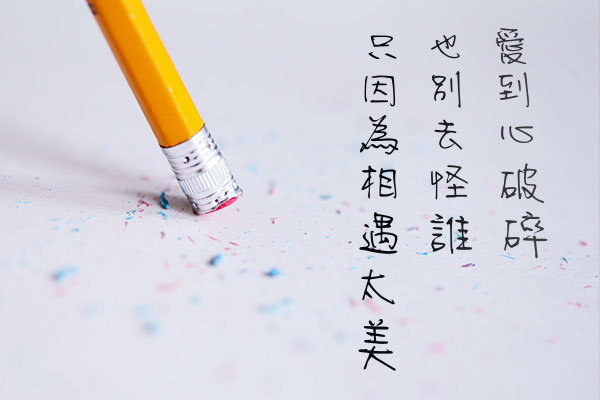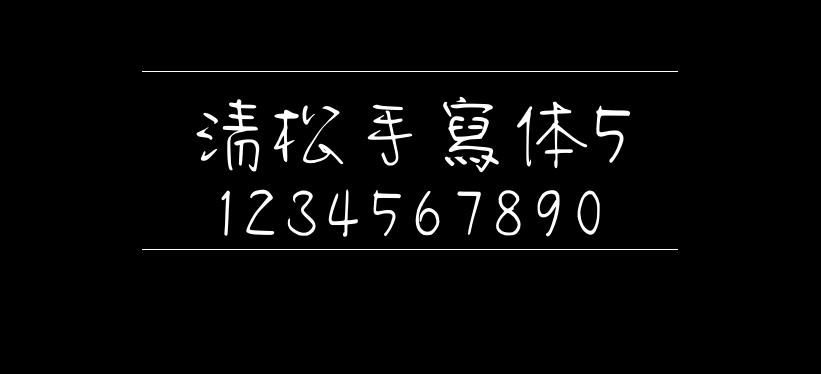
清松手写体5
清松手写体5(JasonHandwriting5、清松手寫體5)是游清松推出的第5套手写字型,作者在稿纸上用原子笔手写,透过“守写字”网站产生出初稿字型档,再字体软件制作加工而成的手写字型。
清松手写体5为手写字型,没有一般电脑字型的生硬感,多了几分手写般的自然感。不论是中文、英文、符号数字,适合在电脑屏幕上阅读、排版、打印出来效果也很棒!